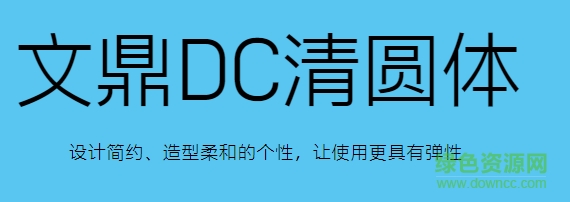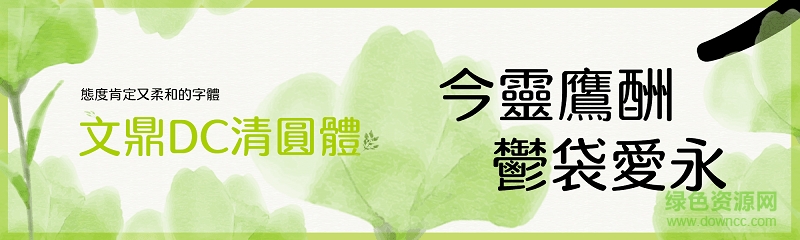
文鼎DC清圓體
文鼎清圓體是文鼎科技全新推出的中文簡體,字跡清淡簡約,更人活潑舒適的視覺體驗,文字端正秀氣,讓你的平面設(shè)計更具獨特美感,歡迎大家來綠色資源網(wǎng)免費體驗!
文鼎DC清圓體官方介紹
設(shè)計簡約、造型柔和的性格,讓使用更具有彈性!
清圓體
態(tài)度肯定又柔和的字體!
文鼎DC清圓體字體特色
不執(zhí)于程序,拋開工具,一切以草圓為零,從頭開始,沒有預(yù)設(shè),先放松,在緊縮!
以九宮格做均衡設(shè)計值控制,在1000×1000的規(guī)格中,以寬920、高910為字面,讓字體視覺更方正。
采非半圓的端點處理,感受到肯定的態(tài)度不模糊,也加強似黑體的縣檔案不魯鈍。